货币符号
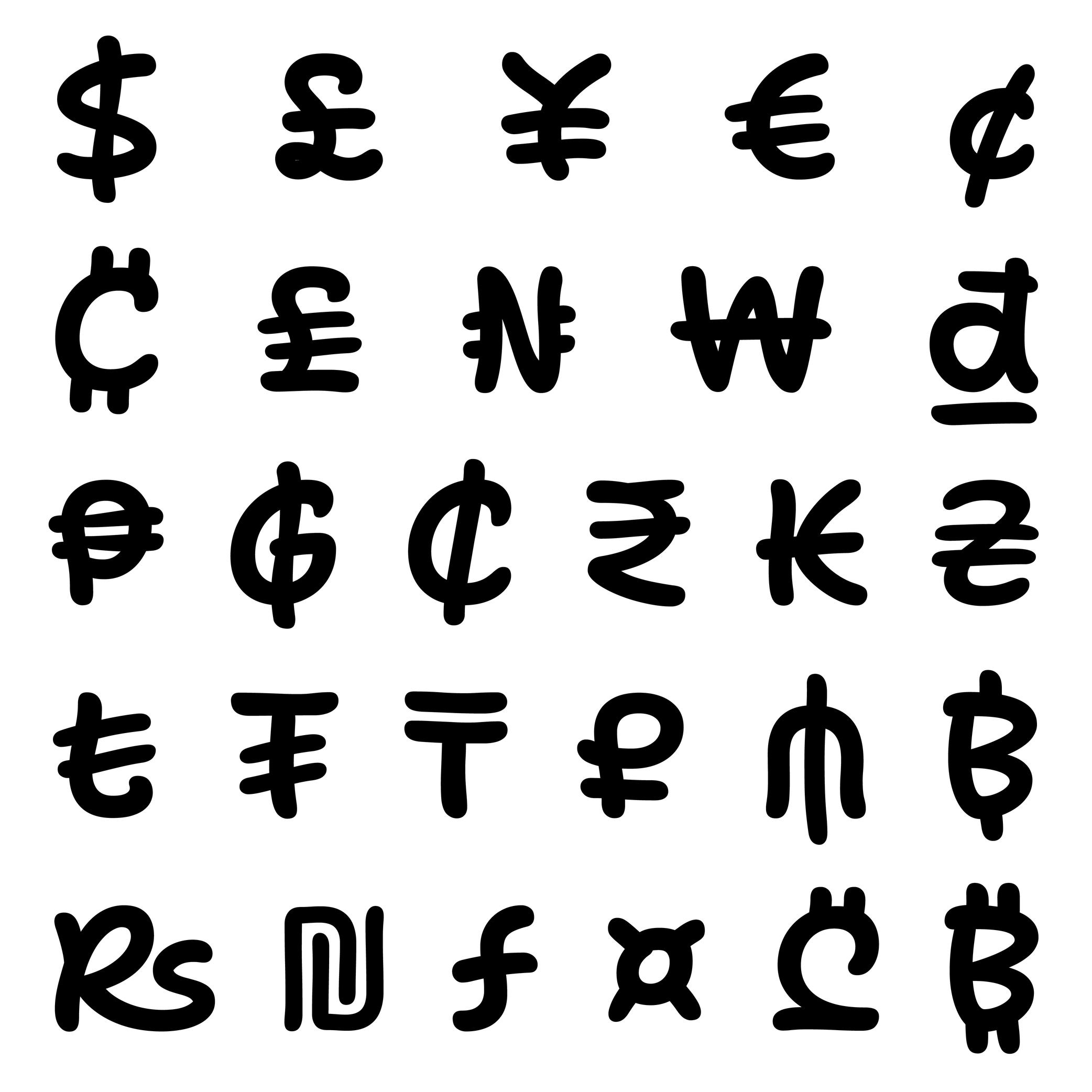
每个货币符号都有相同的功能:为数字附上经济的价值。它们都有自己的历史和演变过程。有一些消失了,或根据不同社会的需求被修改了。
它们大部分都是基于拉丁字母加上不同程度的修改而来的(美元 $,欧元 €,越南盾 ₫)。有一些直接使用字母(瑞士 CHF)或者特定的字符(中国的人民币 元)。
设计
货币符号的设计需要和数字保持和谐,因为它们经常在一起被使用。
在一个有着多个字重的字体家族中,最细的样式中的货币符号可以轻松地展现所有笔画和细节。但是随着字重的增加,这些就会变得困难,尤其是太多细节被加粗后可能会把符号变成一团死黑,无法辨认。最常用的解决方案是把符号简化,移去一些不那么重要的细节,从而保持易认性。